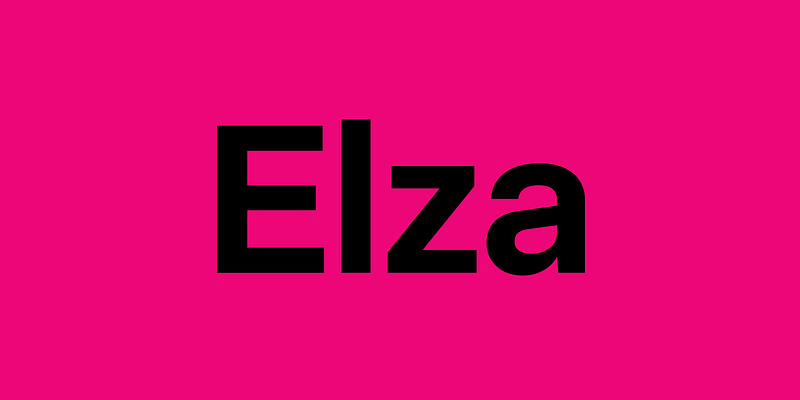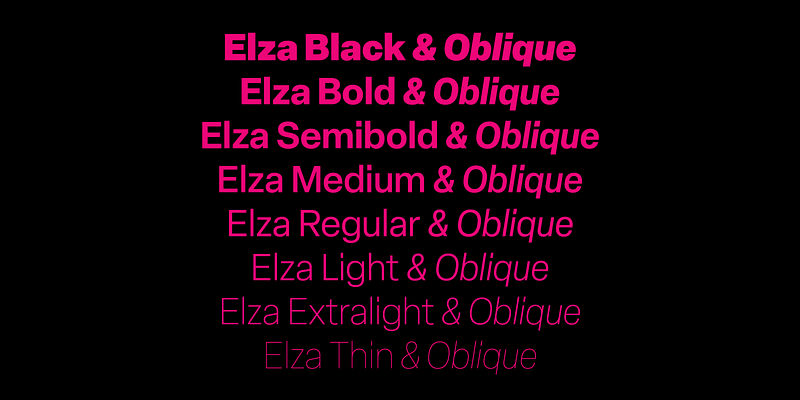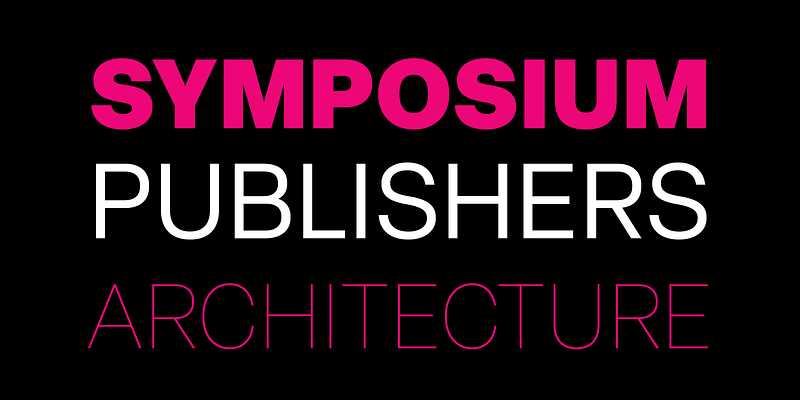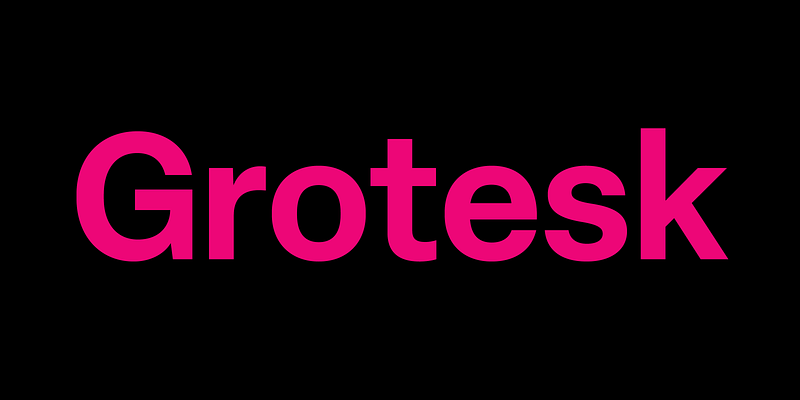
Elza는 어떠한 개인적인 특성이나 구별되는 특징이 없는 글꼴 패밀리를 제작하려는 의도를 바탕으로 한 서체입니다. 이 글꼴은 진정한 이탤릭체 대신 비스듬한 모양의 버전을 제공하며 그 폭은 각각의 로마체 버전보다 훨씬 더 압축되어 있어 함께 사용할 때 더 잘 돋보입니다. 8가지의 두께, 3가지의 폭 및 2가지의 광학 크기로 총 58가지의 글꼴로 구성된 현재까지 Blackletra의 라이브러리에서 가장 큰 글꼴 패밀리입니다. 각각의 글꼴에는 약 900가지의 글리프가 있으며 광범위한 언어 지원과 더불어 작은 대문자, 표 형식 및 올드 스타일의 그림과 같은 OpenType 기능, 그리고 소문자 “/a”(1단)의 대체 문자를 제공합니다. Elza는 두께, 폭 및 경사 축과 함께 다양한 버전을 제공하는 Blackletra의 첫 번째 서체입니다.